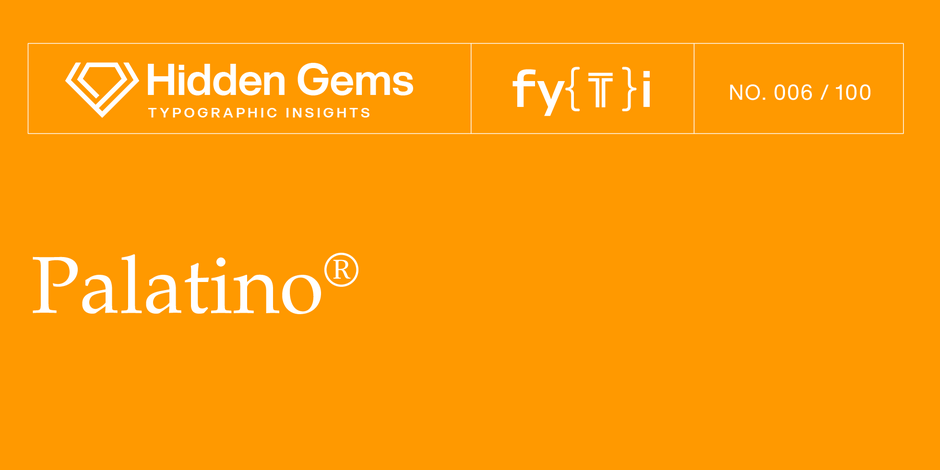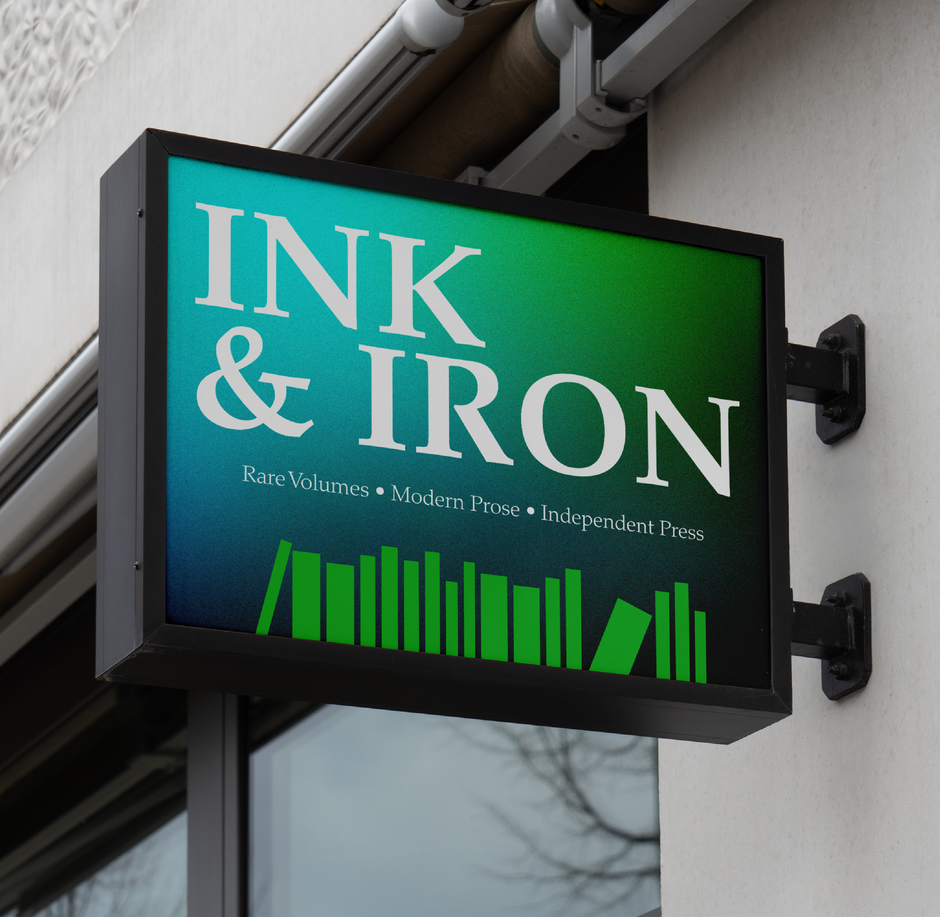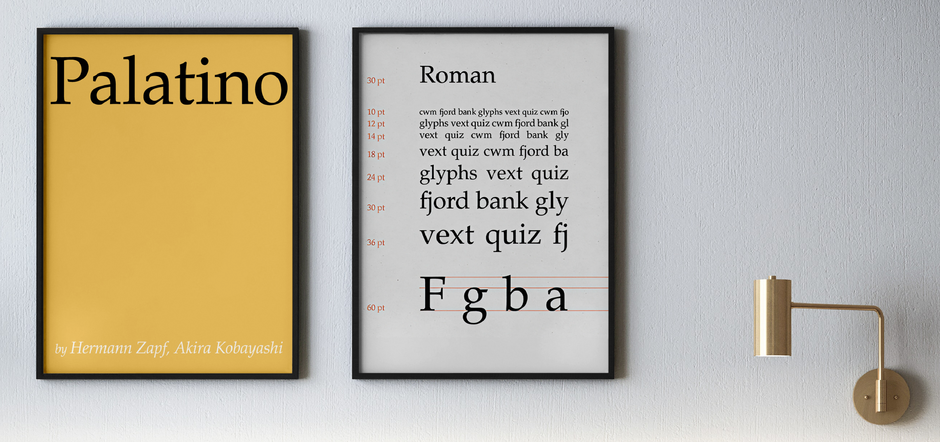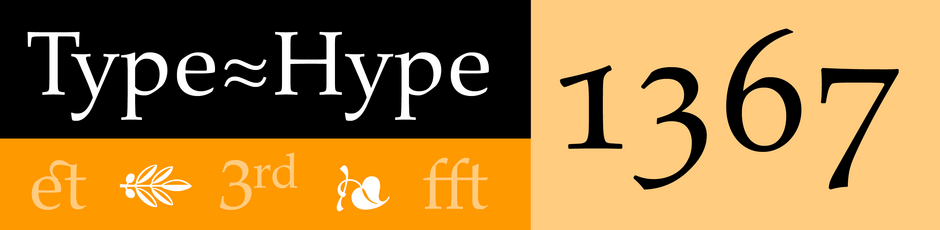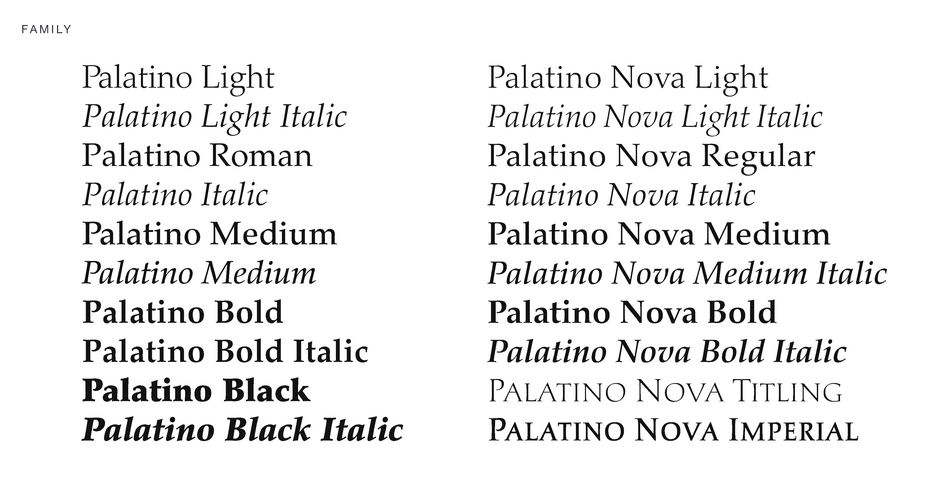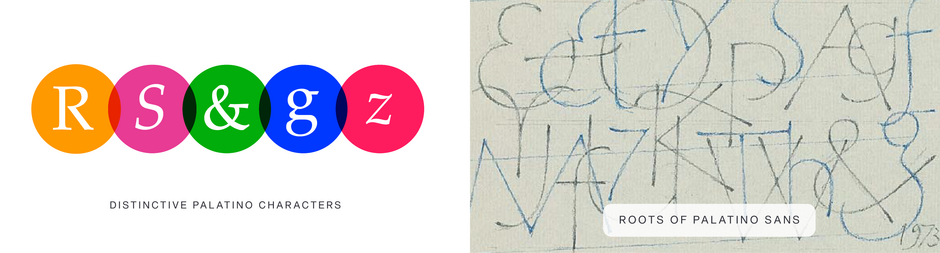
Le joyau caché Palatino®
FONDERIE : Linotype
CONCEPTEUR : Hermann Zapf et Akira Kobayashi
CLASSIFICATION : Serif Old Style
Le Palatino diffère des modèles typiques de l'ancien style en ce sens que ses guichets sont ouverts et que ses proportions sont quelque peu élargies. Ces caractéristiques permettent au Palatino de rester lisible dans divers environnements d'impression et de lecture.
ANCESTRY
- Le Palatino original a été publié en 1950, sous la forme de polices de caractères métalliques de poche. Le Palatino a ensuite été adapté à la composition mécanique sur la machine Linotype et est devenu l'un des caractères les plus utilisés du XXe siècle.
- Ce caractère porte le nom de Giambattista Palatino, un maître de la calligraphie de l'époque de Léonard de Vinci. Le Palatino est une police de caractères basée sur les formes classiques de la Renaissance italienne.
- Palatino Nova est le résultat d'une collaboration entre Hermann Zapf et Akira Kobayashi. Publié en 2005, il s'agit d'une réimpression du dessin original pour l'imagerie numérique.
- Palatino Nova comprend plusieurs graisses et dispose de jeux de caractères grecs et cyrilliques. La famille comprend également deux modèles de titrage basés sur des caractères Zapf antérieurs conçus pour la composition sur métal.
- Associez Palatino et Palatino Nova à des polices sans empattement plus simples pour créer un contraste. (Les polices avec empattement à l'ancienne ont beaucoup de caractère.) Pensez également à les associer à des polices sans empattement modernes et épurées, telles que Helvetica® Maintenant, Nouveaux fruits et légumes ou Avenir® Next. Cela créera un équilibre entre tradition et fraîcheur.
- Considérer Palatino Sans pour une association subtile et complémentaire. Veillez simplement à ce que les poids utilisés soient nettement différents les uns des autres.
- Utilisation Palatino Nova pour le corps du texte et des polices plus décoratives pour les titres. Pour l'affichage ou les titres, vous pouvez choisir une police de caractères plus distinctive ou décorative telle que Olive antique, DIN Suivant ou Souvenir du CCI.
Palatino Nova est essentiellement une police de texte destinée à la mise en place d'un corps de texte distinctif. Si vous recherchez des caractères d'affichage plus lourds, les polices Palatino originales devraient être envisagées.